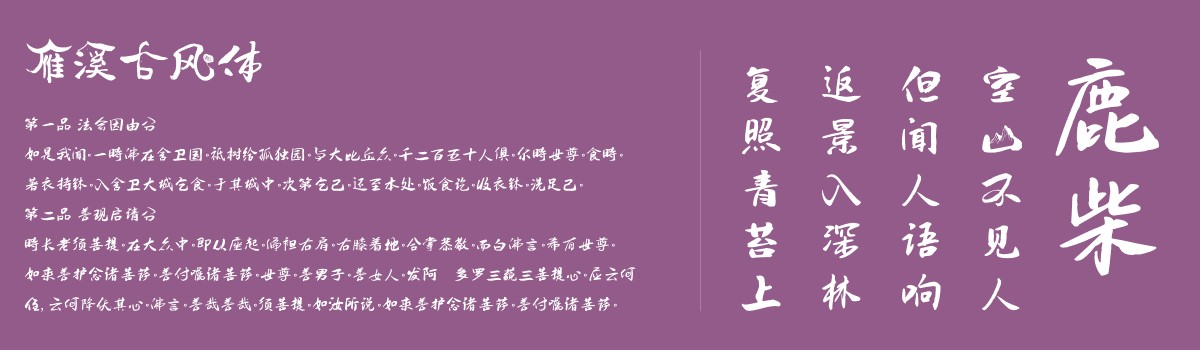
雁溪古风体
写字是一种修行,如登高山,如禅坐在。
一笔一划间可以沉淀心灵,一横一竖、一撇一捺,造就了中式美学。
它是融于生活,中国文化最美的精华。
"柴米油盐酱醋茶,琴棋书画诗酒花"
这,才是有心有情的人生。
雁溪古风村落的特性,简约而唯美,叶根友先生以古村落特有的屋檐元素进行创作,像雁溪何八公殿的檐阙一般,独特的字体文化蕴涵着天马行空的魅力。